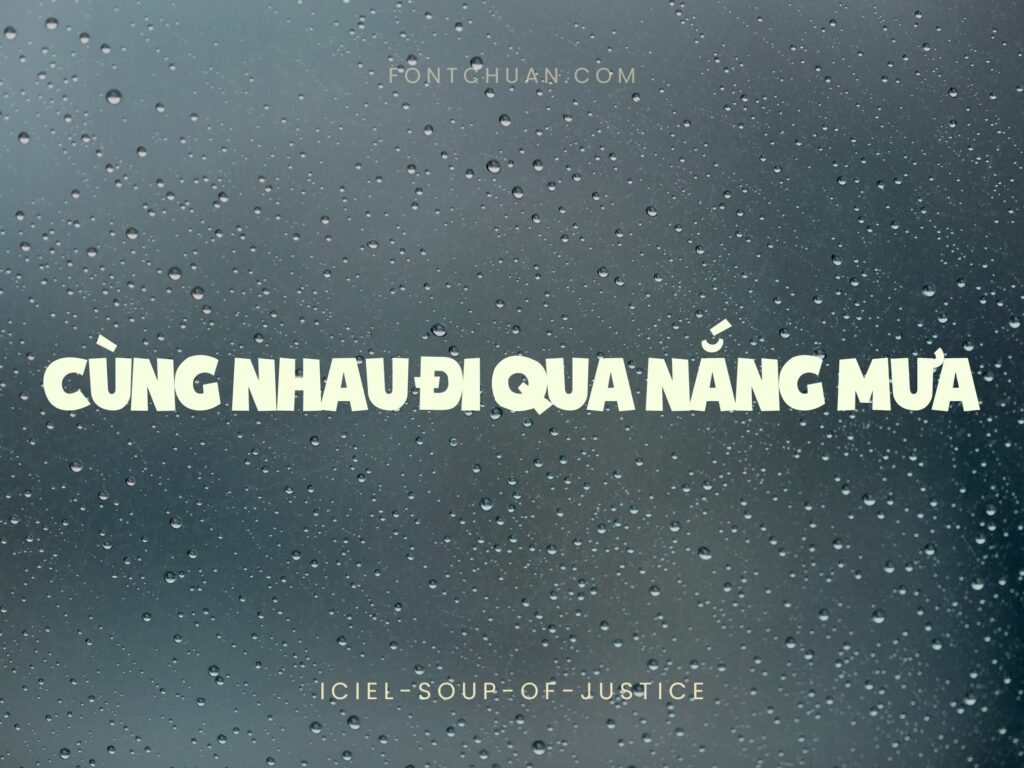
Font iCiel Soup Of Justice Việt Hóa
Soup of Justice là một kiểu chữ đậm và vui nhộn, được thiết kế bởi Omen Type. Font này mang phong cách hoạt hình với các ký tự dày dặn và hơi ngộ nghĩnh, tạo cảm giác thân thiện và năng động. Đặc biệt, Soup of Justice đã được Việt hóa bởi iCiel, hỗ trợ tiếng Việt cùng nhiều ngôn ngữ khác, đáp ứng nhu cầu đa dạng của người dùng. Font này được chia sẻ rộng rãi trên các trang web như FFonts.net và Dafont.com, giúp cộng đồng thiết kế ứng dụng dễ dàng trong các dự án của mình.
Về đặc điểm thiết kế, Soup of Justice sở hữu các ký tự đậm, hình học với phong cách vui tươi và năng động. Font này phù hợp cho các thiết kế như tiêu đề, poster, logo, bao bì sản phẩm và các ấn phẩm truyền thông cần sự nổi bật và cá tính. Ngoài ra, Soup of Justice còn thích hợp cho các ngành nghề như quảng cáo, ẩm thực, thiệp cưới và spa, cùng các sự kiện đặc biệt như lễ hội, sinh nhật, Halloween và Trung thu.